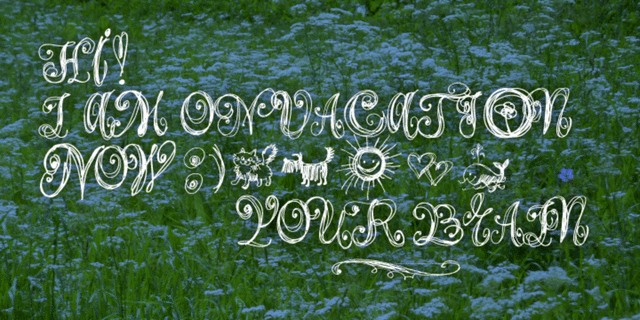
Airy — чрезвычайно легкомысленный летний шрифт без малейшего намёка на какую-нибудь глубокую идею. Будучи составленным из множества небрежных, но кудрявых букв, он создаёт каждый раз иную, но всегда кружевную фактуру набора. К буквам прилагается набор не менее легкомысленных картинок, и вместе они составляют чудесную имитацию какого-нибудь бестолкового, но милого девичьего дневника. Дизайнер – Александра Королькова. Шрифт выпущен компанией ParaType в 2010 году.
веселый, смешной, озорной, игривый, наивный, кудрявый, манерный, характерный, оригинальный, самобытный, неординарный, ажурный, кружевной, мажорный, инфантильный, легкомысленный, воздушный, глупый, цветочный, летний, интимный, сентиментальный, ветренный, прозрачный, девчачий, кучерявый, сказочный, детский, новогодний, хрупкий, весенний, праздничный, дурацкий, прелестный, симпатичный, счастливый, радостный
реклама, развлечения, выставка, цветы, игрушка, завивка, брошка, бижутерия, украшение, аксессуары, одежда, парикмахерская, хенд-мейд, сувенир, утренник, сад, клумба, дневник, принцесса, сказка, собачка, болонка, Новый Год, игра, зоопарк, зоомагазин, животные, отдых, лагерь, весна, праздник, бабочки, платье, школьница Стилистика: